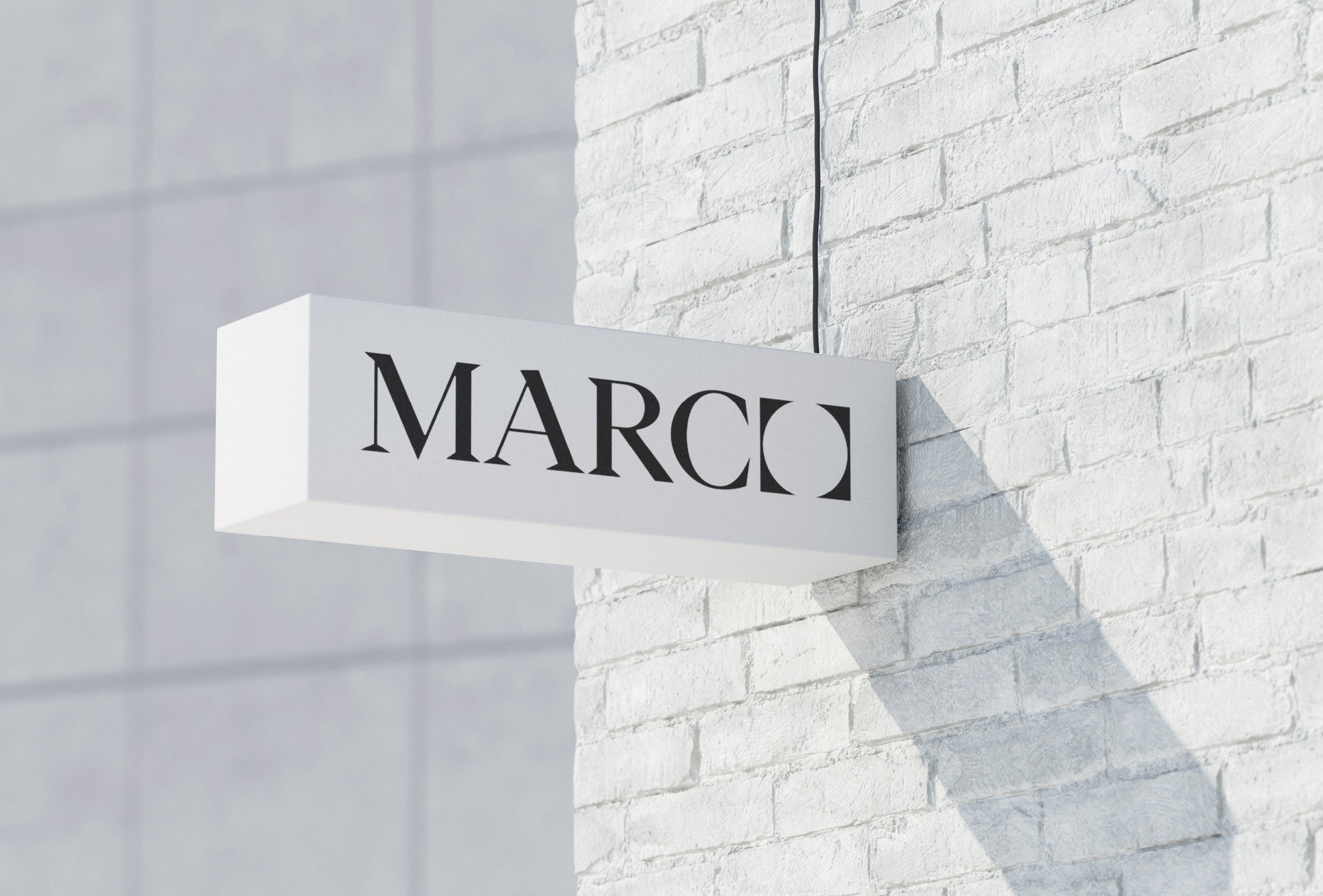
Eva Marco Estudio est une entreprise de design d'intérieur qui travaille dans des espaces publics et privés, avec un accent particulier sur les maisons privées, en s'occupant des projets d'architecture et de rénovation jusqu'à la décoration.
Le studio cherche à améliorer la qualité de vie des gens et à les aider à construire leur maison idéale. Pour cela, le designer principal crée des espaces esthétiques, lumineux, harmonieux, accueillants et surtout fonctionnels, en offrant un service entièrement personnalisé et en s'engageant à intégrer des œuvres d'art et des objets de design dans ses projets de décoration.
La célèbre décoratrice d'intérieur espagnole Eva Marco Escribano, qui a fondé son studio il y a plus de 18 ans, nous a confié la mission de développer une nouvelle identité visuelle pour son studio, à la hauteur de la qualité de ses projets. Leur objectif était d'attirer de nouveaux clients et de développer des projets plus ambitieux et ambitieux.
Le résultat est une marque qui met en valeur le changement, pour représenter la transformation et l’amélioration qu’un espace subit à travers la vision et le travail du designer d’intérieur.
Le nouveau logo se compose d'un mot-symbole formé uniquement du mot Marco, dont la dernière lettre a été modifiée pour former un « O » inversé projeté dans un espace carré. Nous souhaitions ainsi donner plus de relief au nom de famille, en exploitant sa force et sa simplicité, afin de créer une identité davantage centrée sur la marque du studio que sur la personne.